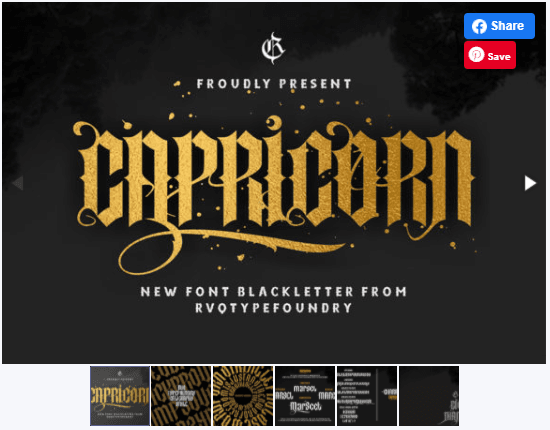
Capricorn Font
Capricorn - это стильный, элегантный и винтажный шрифт blackletter. Он обязательно поможет вам создать самый впечатляющий дизайн, который будет вдохновлять силой и изысканностью!